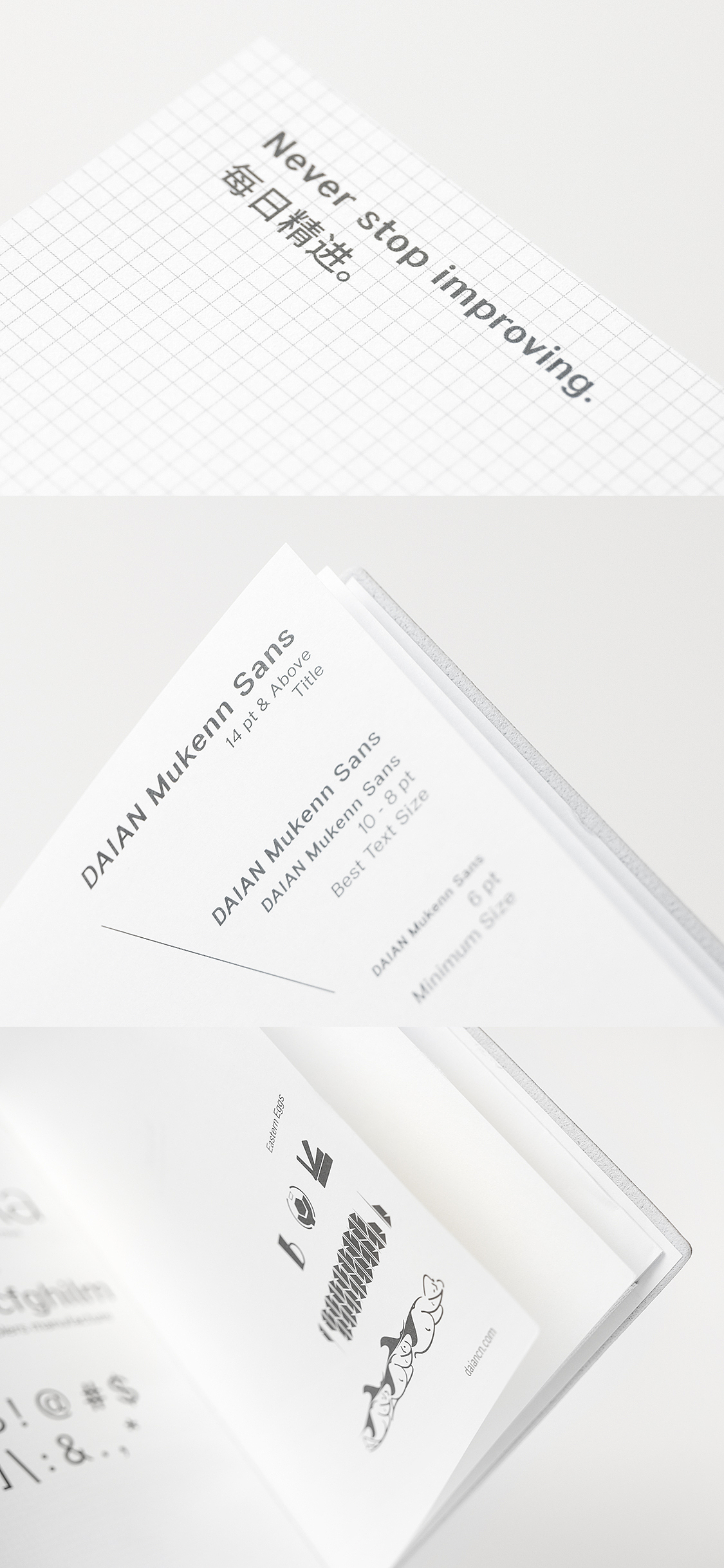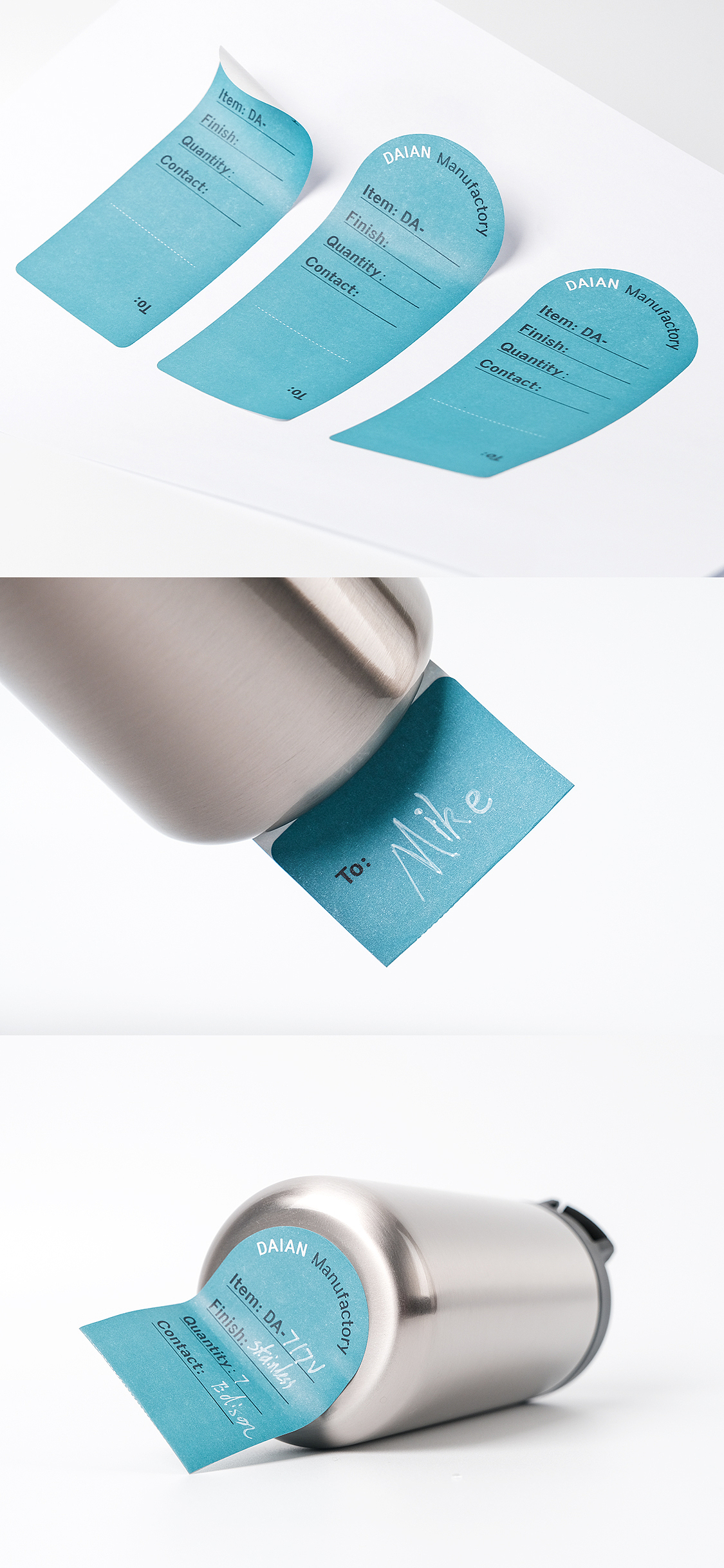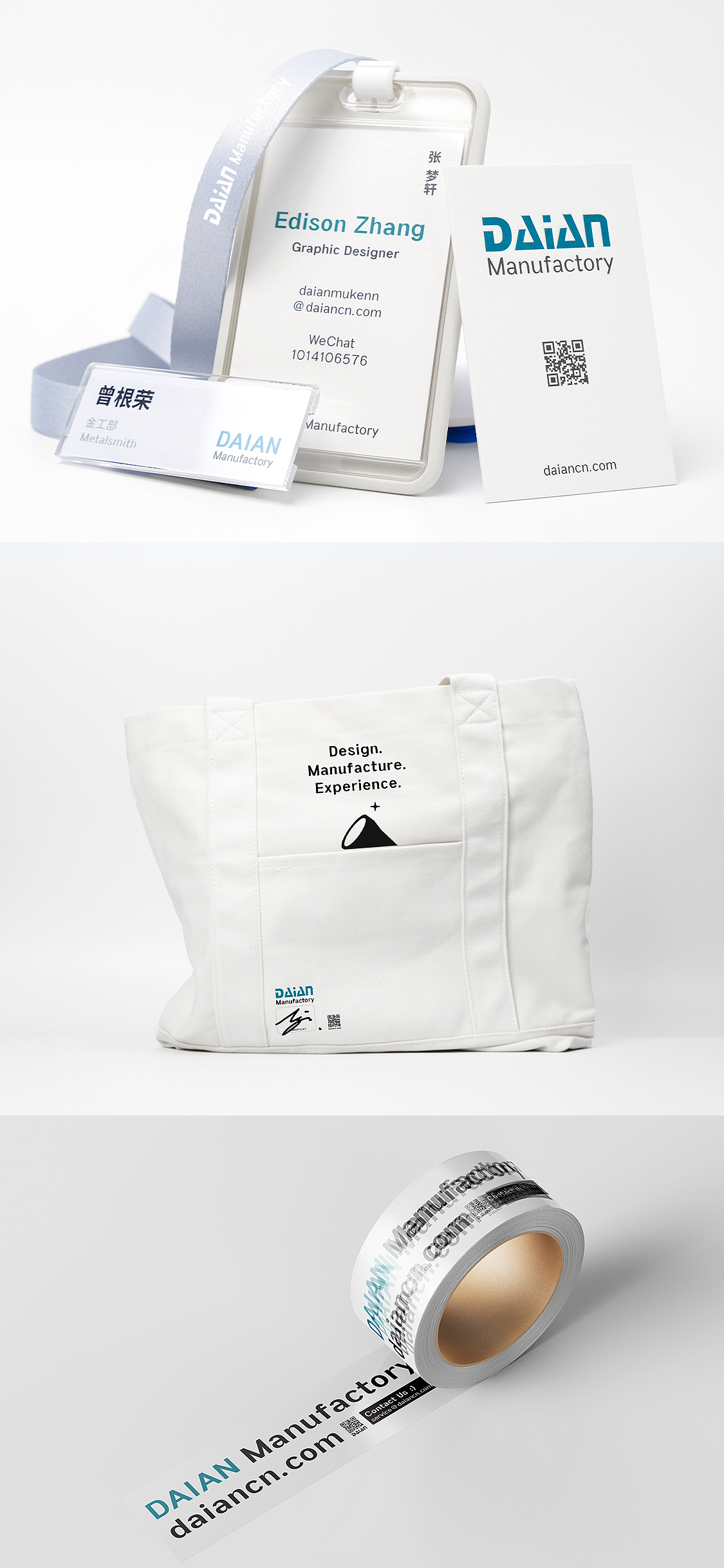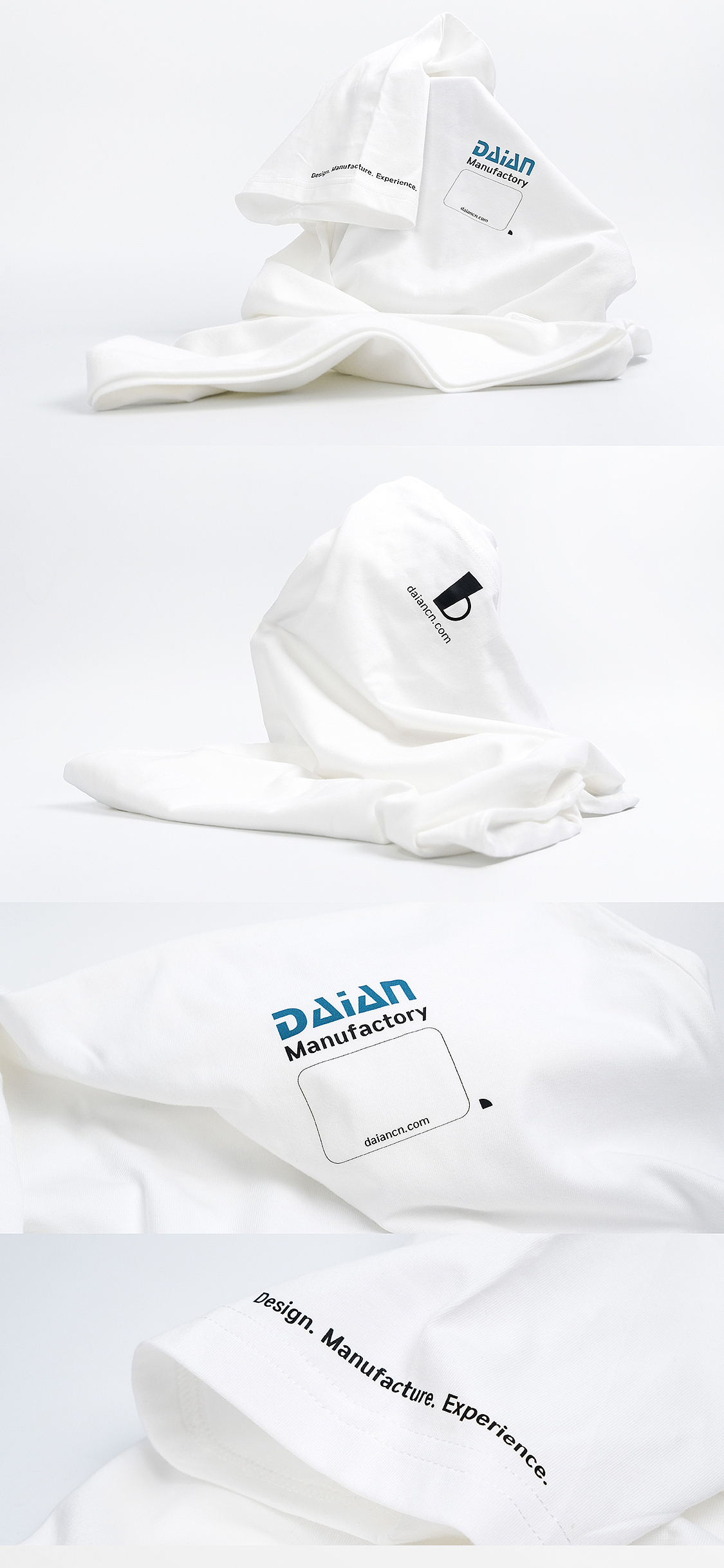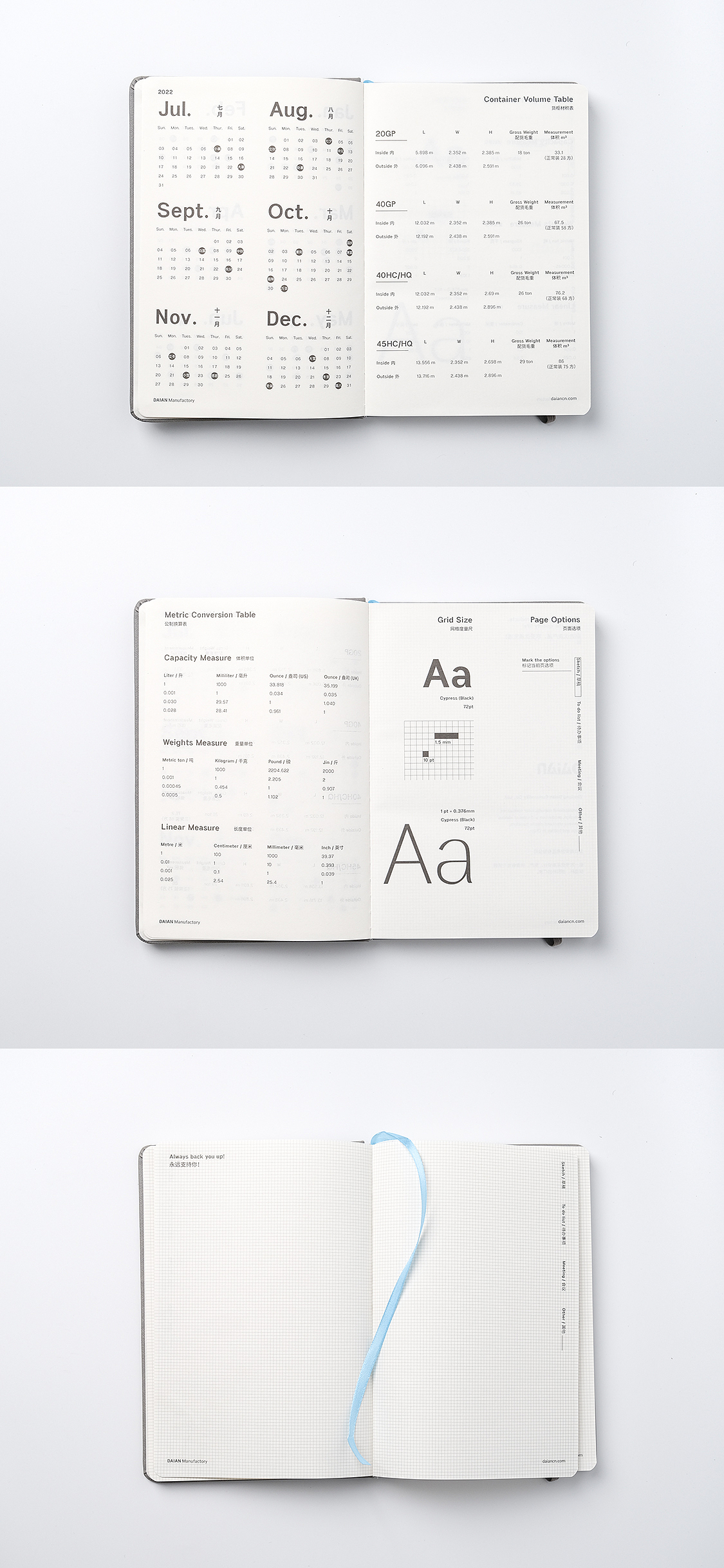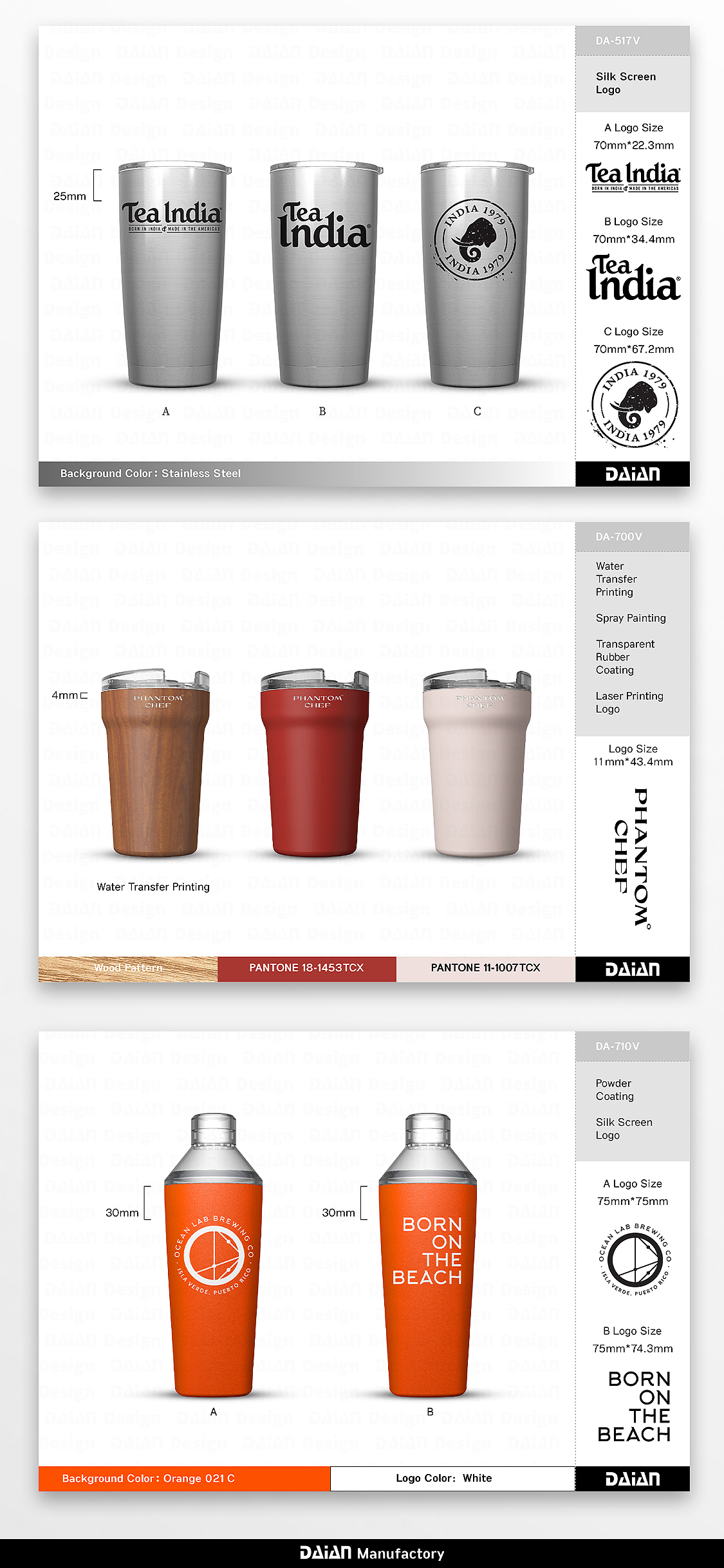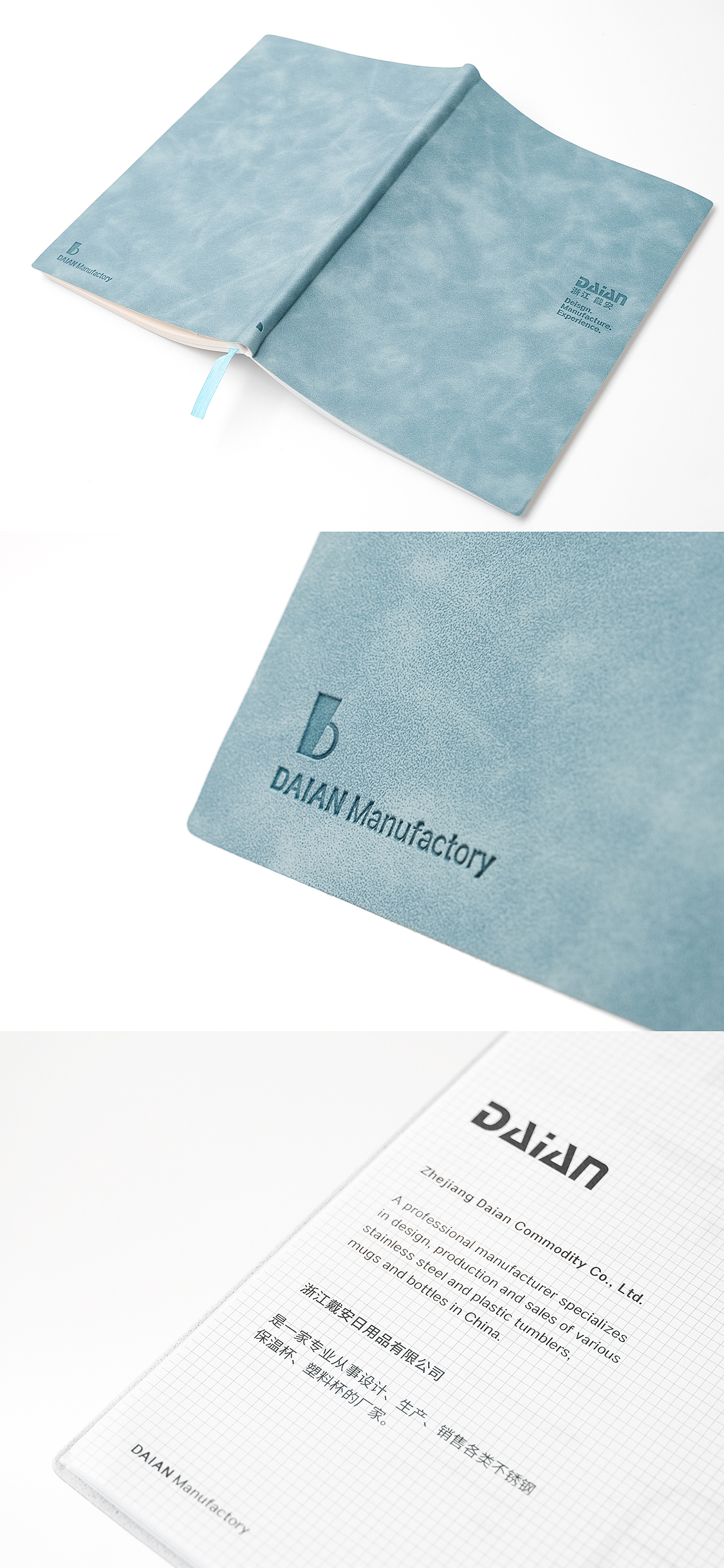
DAIAN Mukenn Sans 1.0
5-6月给公司做的一款西文无衬线体
公司为代工厂,主要是外贸,平时应用到西文的场景比较多,拥有一款专属西文字体是刚需。
设计的初衷就是为了简单好用,再稍微有点趣味就OK了。
本次字体应该分布在办公VI(笔记本,样品贴纸,卡片,封口胶带,短袖,帆布袋,PPT)以及客户定制产品效果图上。
这款字体最有趣的是利用自由合字与可变字体的功能制作的小彩蛋,真是上班摸鱼的利器。